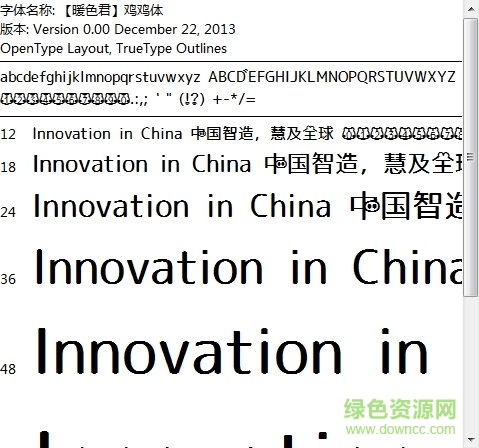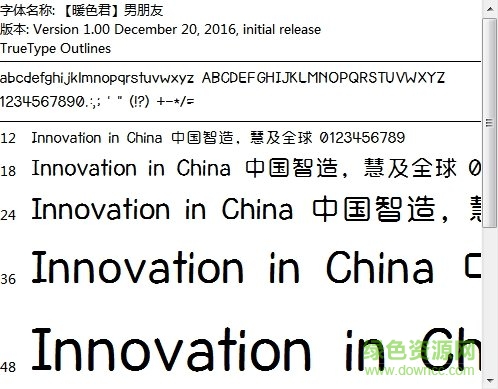
暖色君的男朋友字體
男朋友ttf字體是暖色君新浪微博分享的一款特色字體,是一款有著各種干凈純粹的的手寫字體,讓你的文字顯得更加活潑,給人比較有趣的視覺閱讀體驗,綠色資源網(wǎng)誠意推薦!
蘋果暖色君男朋友體
暖色君的男朋友字體是支持蘋果手機、蘋果電腦、安卓手機等使用的中文字體,原名暖色君的雞雞體,該字體造形奇特,效果特殊,適用于產(chǎn)品設(shè)計、包裝印刷、報刊雜志、繪畫創(chuàng)作等方面。